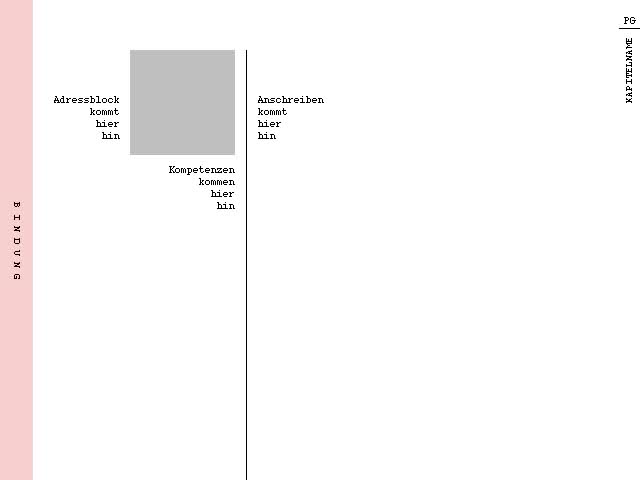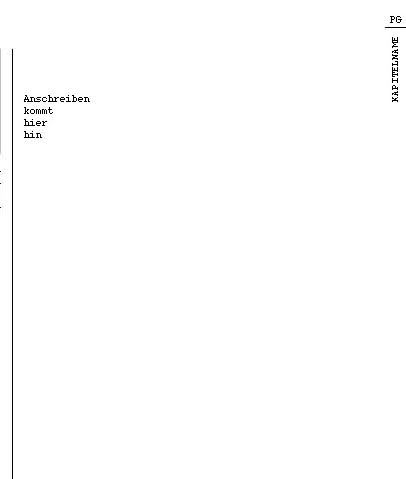
Partner für Frutiger gesucht
Gleich zum Anfang wende ich mich gleich mit einem kleinen Problem an Euch. Momentan bin ich dabei, eine Portfoliomappe zu bauen, um in Zukunft meine Arbeiten und Illustrationen zu zeigen.
Das wäre ja an sich nicht das Problem- 98% der Mappe bestehen ja nur aus Bildern. Allerdings findet sich in der Mappe auch ein Anschreiben, das mir jetzt einige Probleme bereitet, da zur Linken eine kleine "Kompetenzenübersicht" stehen soll, die ich optisch doch einigermaßen vom Anschreiben trennen möchte. Ich habe zwar schon mit der Schriftgröße herumprobiert, aber bin damit nicht wirklich auf einen grünen Zweig gekommen.
Hier mal ein schnell zusammengeschusterter Dummy der Seite:
Das Anschreiben wollte ich in Frutiger (45 Light, 10 oder 11 pt, je nach Länge) setzen. Die "Kapitelnamen" (mir ist der Fachbegriff jetzt entfallen) und die Pagina sind in DIN gesetzt, um einen Kontrast zum eigentlichen Text zu schaffen (und ich diese Schrift einfach liebe).
Mein Problem ist jetzt eben die "Kompetenzenübersicht"- ich wollte zwar die DIN wieder aufgreifen, aber wirklich "rund" ist das Ganze in meinen Augen nicht.
Wenn jemand einen Tipp für mich hätte, wäre ich ihm (oder ihr) natürlich sehr dankbar. Eine serifenlose Schrift wäre mir persönlich am liebsten, aus irgendeinem Grund bin ich kein großer Freund von Serifen. Dürfte vielleicht auf meine "Computerfixierung" seit der Kindheit zurückzuführen sein.
PS: Ich kann mir denken, dass der generelle Aufbau des Ganzen sicher gegen einige "Grundlagen" des Seitenaufbaus verstößt. Ich bitte aber um Nachsicht, da der Bereich "Typografie" für mich noch ziemliches Neuland darstellt und ich gerade erst meine ersten vorsichtigen Schritte auf diesem Gebiet mache. Aus diesem Grund suche ich ja auch Euren Rat- denn nur von Profis kann man wirklich lernen.
EDIT: Aus irgendeinem unerfindlichen Grund, trotz Verkleinerungsfunktion von TinyPic, schneidet die Software den Kapitelnamen und die Pagina ab. Deshalb hier noch ein Bild der "Seitenleiste":
Die DIN und die Frutiger passen nicht zusammen: Die Frutiger ist eine dynamische (humanistische), die DIN dagegen eine geometrische (konstruierte) Schrift. Darum wirkt es auch nicht „rund“.
Statt der DIN würde ich einfach mal die kursive Frutiger ausprobieren.
Und wenn Du nur keine klassischen Antiquae magst, vielleicht sowas:
Das, was du Kapitelnamen nennst, dürfte der sogenanne „lebende Kolumnentitel“ sein.
Zur Frutiger light vielleicht die Frutiger Condensed bold bzw. black in deutlich abweichender Schriftgröße?
Danke für den Tipp mit der Caecilia, werde ich beizeiten mal ausprobieren.
Eventuell werd' ich aber doch eher auf die DIN als Brotschrift setzen und mit ihren Schnitten experimentieren... die Lektüre des Buches "NSCI" hat mir überraschend vor Augen geführt, dass die DIN eigentlich eine sehr angenehme Schrift für Fließtext ist- zumindest für mich.